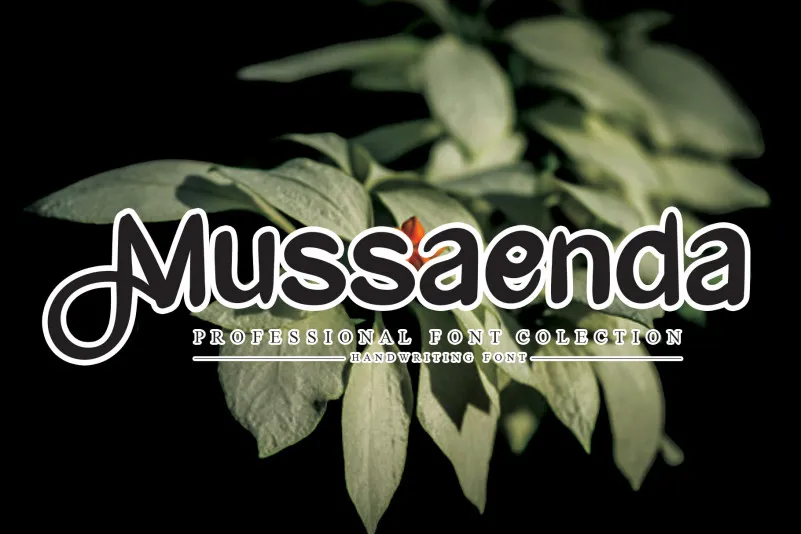
Mussaenda Script Font – Download Grátis
A Mussaenda Script Font é uma elegante caligrafia com traços fluidos e sutis, perfeitamente projetada para se destacar no design editorial. Este estilo de fonte manuscrita mantém os contornos delicados dos antigos estilos de escrita ao mesmo tempo contemporâneo e atual. Sua textura suave e sua capacidade única em adaptar-se a diversos formatos fazem dela uma escolha ideal para designers que buscam dar vida ao texto com um toque pessoal. Com um design perfeitamente equilibrado, esta fonte é perfeita para aqueles desejosos de adicionar personalidade aos seus trabalhos, seja em revistas, websites ou livros. A Mussaenda Script Font proporciona uma experiência única e envolvente ao leitor, oferecendo um equilíbrio entre a elegância do passado e a modernidade inovadora. Ela é um recurso invaluable para qualquer designer que procura manter sua identidade visual forte através de textos expressivos.